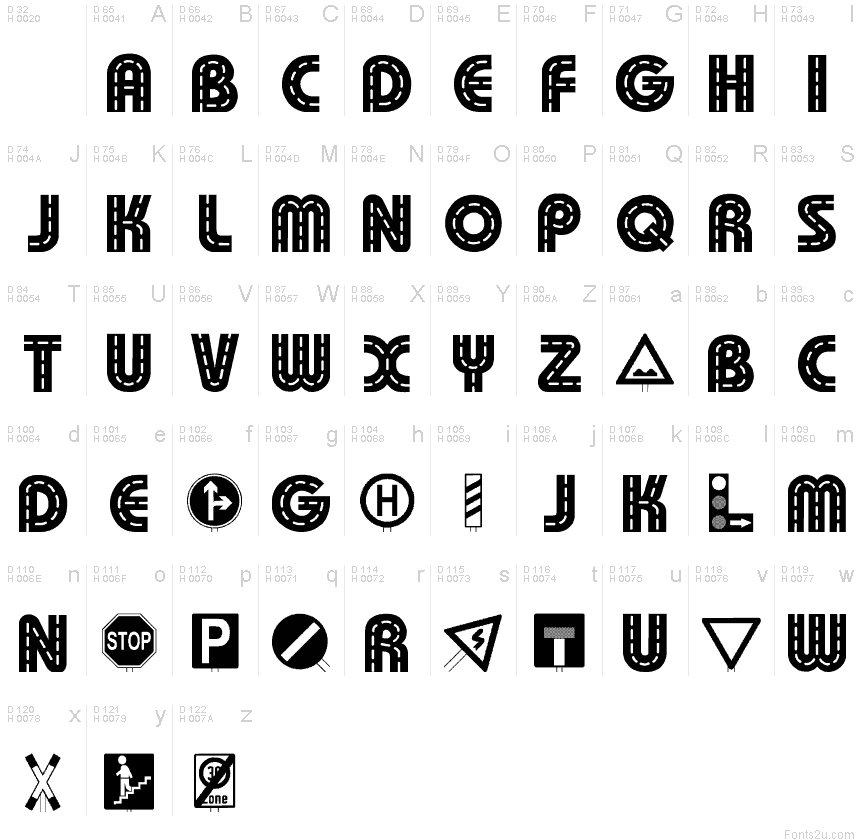
Schilderwald autorstwa Susanne Fiedler to darmowy font typu display, inspirowany znakami drogowymi, o zabawnej, „drogowej” osobowości. Litery czerpią z języka grafiki ulicznej – mamy tu przerywane linie, obramowania znaków ostrzegawczych, pasiaste panele, punkty sygnalizacyjne i groty strzałek – dzięki czemu cały alfabet wygląda, jakby został przeniesiony wprost ze znaków drogowych, a nie zaprojektowany jako zwykły font ozdobny.
Sprawdzi się na plakatach związanych z transportem, ulotkach, w projektach szkolnych, tytułach redakcyjnych i krótkich formach brandingowych, gdzie darmowy font może dodać dynamiki i kierunku. Używaj go w nagłówkach, na okładkach, w monogramach czy krótkich grafikach informacyjnych – zwłaszcza gdy chcesz, aby to litery same opowiadały wizualną historię, bez polegania na dodatkowych ikonach.
Schilderwald
Susanne Fiedler